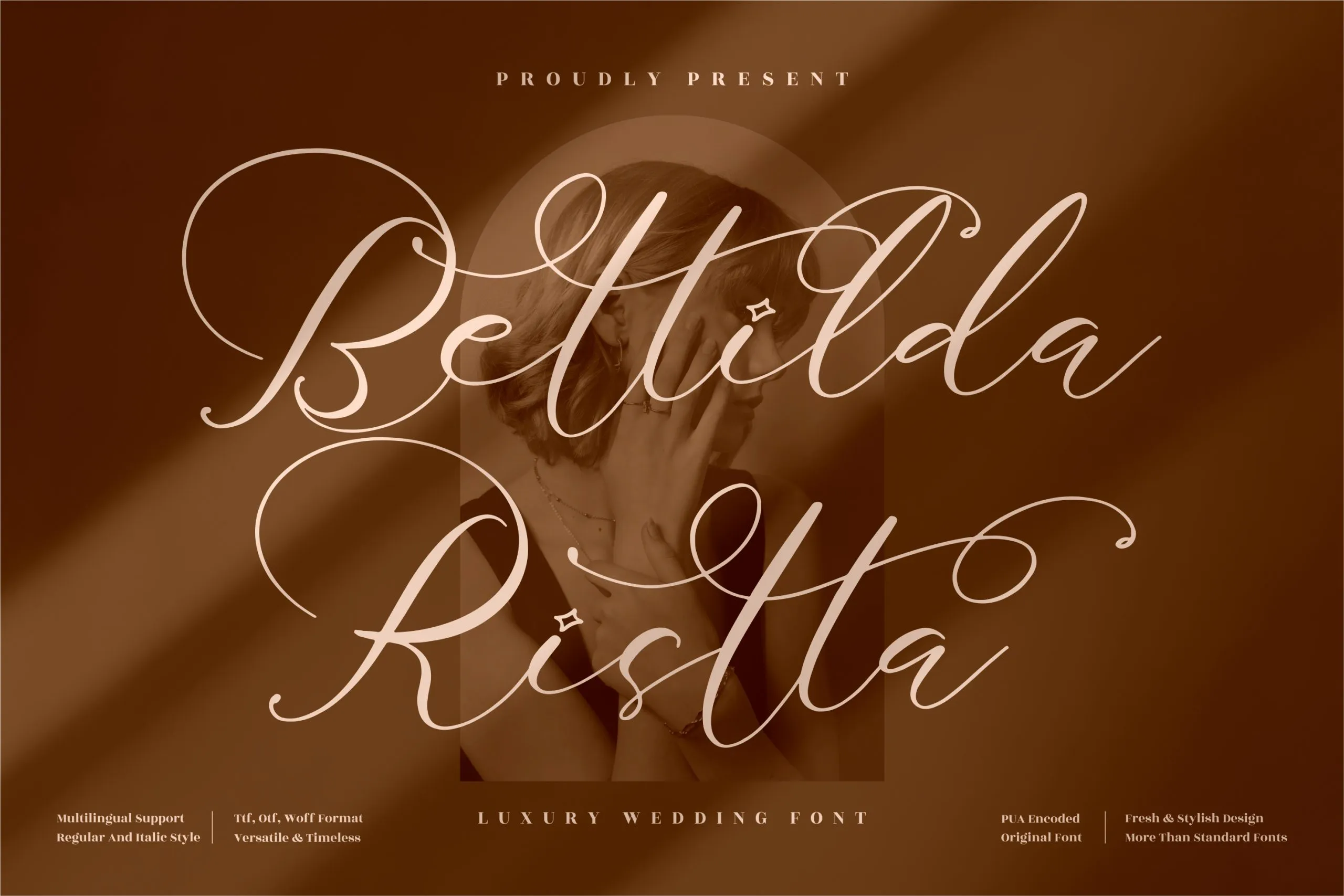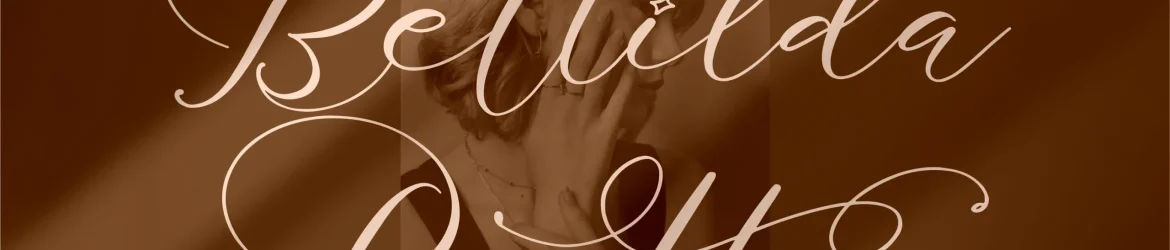
A Bettilda Ristta Font é uma elegante tipografia feita para projetos que exige beleza e romantismo. Desenvolvida pela Perspectype Studio, ela se destaca como um belo tipo de escrita adequado a uma variedade de trabalhos, desde identidades de marca e designs de móveis até etiquetas de embalagens ou selos para presentes, cartões de convite e capas de livros. Suave e delicada, esta fonte elegante pode enriquecer qualquer projeto que precisa de um toque sofisticado e aconchegante. Com sua capacidade única em adaptar-se a uma vasta gama de aplicações, é perfeita para quem procura uma tipografia diferenciada para criar um visual único e memorável em seus projetos criativos.